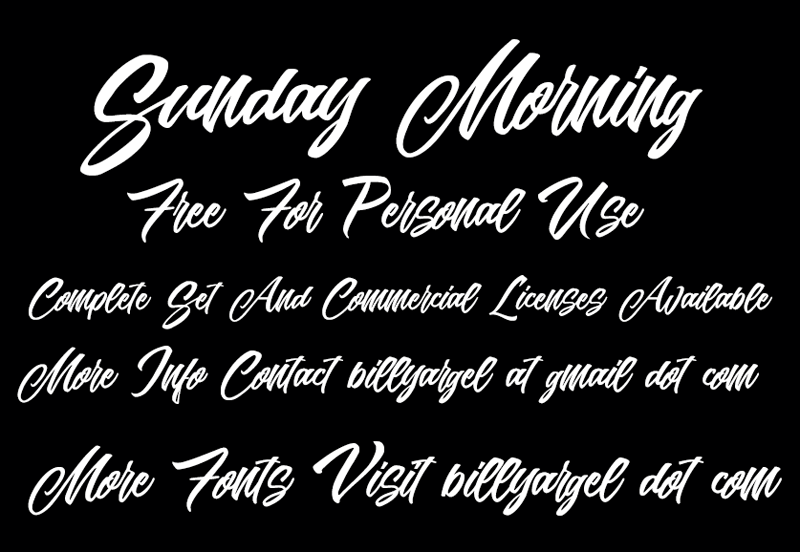
Sunday Morning Font – Download Grátis
A fonte ‘Sunday Morning Font’ é uma mão-direita que pode ser usada gratuitamente para fins pessoais. Para licenciamentos comerciais ou aquisição do conjunto completo, consulte Billy Argel no billyargel.com. É uma fonte de estilo livre e autêntica criada pelo designer Hamilton. Se você está procurando um recurso gráfico único que ofereça um toque delicado e natural à sua tipografia, ‘Sunday Morning Font’ é definitivamente o tipo de material que você precisará. Esta font foi projetada para uma utilização pessoal sem custos adicionais; para fins comerciais ou aquisição do conjunto completo, visite billyargel.com para mais informações. Com suas linhas elegantes e harmoniosas, esta fonte é perfeita para textos de notas manuscritas, cartões de felicitações e até mesmo o texto dos seus documentos pessoais. Visite www.billyargel.com ou siga eles em Facebook.com/billyargelfonts se estiver interessado em outros recursos gráficos criados por Hamilton.